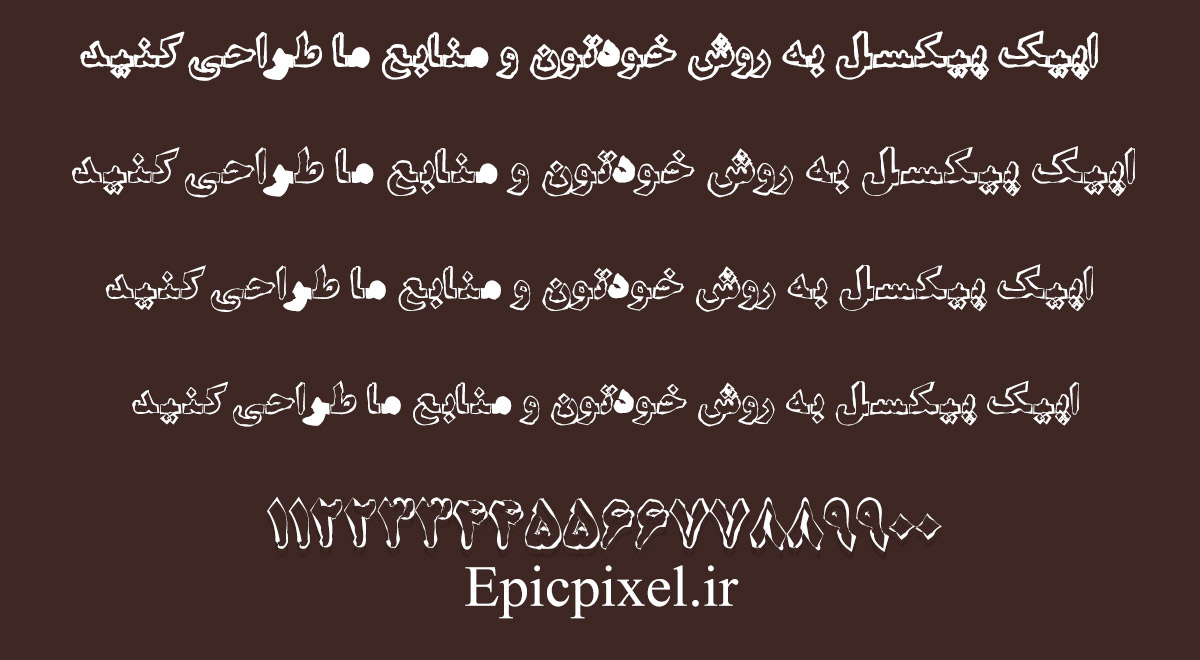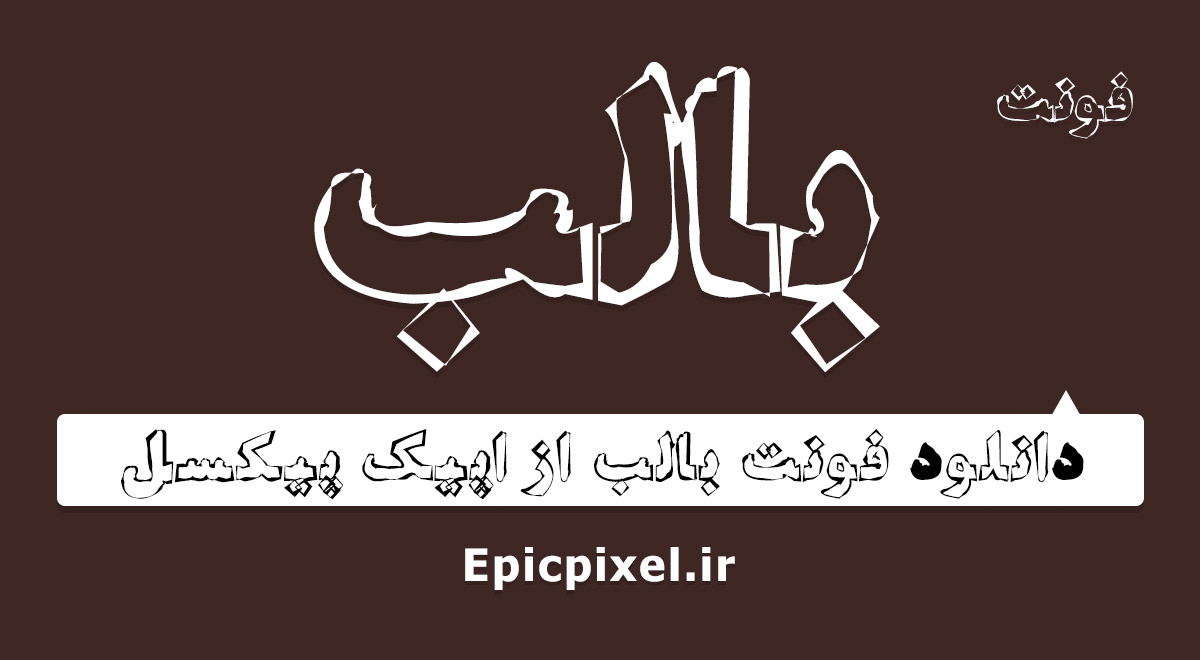
فونت بالب فارسی
دانلود فونت Bulb فارسی Font بالب |
| فونت | فونت سیاوش بالب رگولار Font SI47ASH Bulb Regular |
فونت های سیاوش کلا فونت های عجیب غریبی هستند بیشتر کانسپچوال هستند تا تایپ فیس